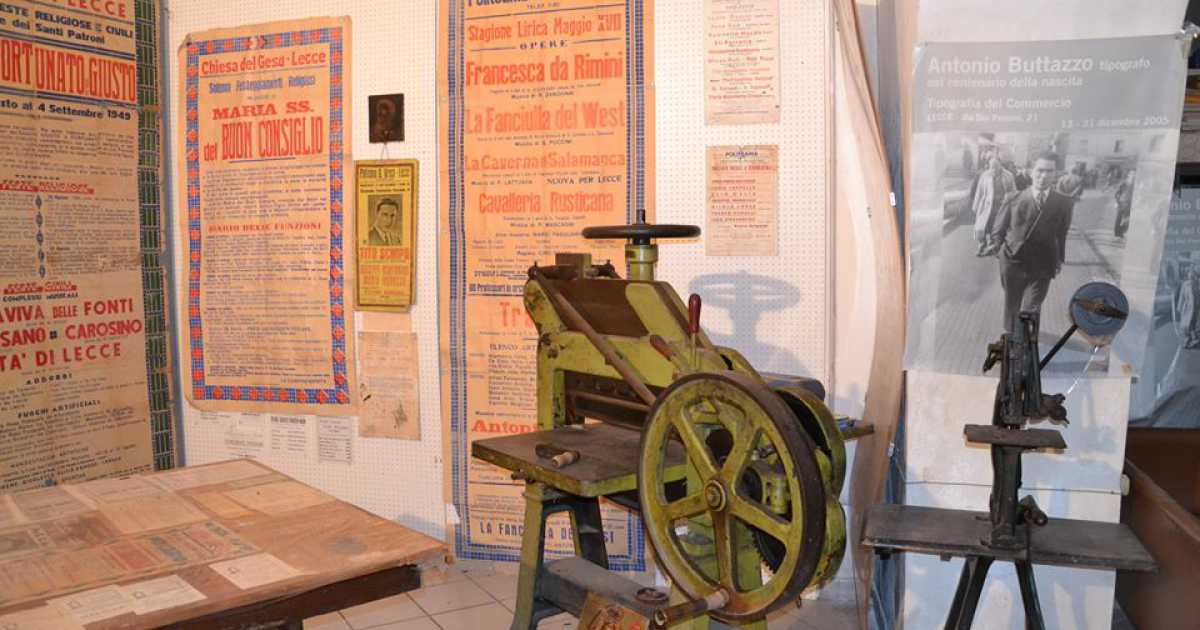
LECCE – Caratteri mobili, odore di inchiostro, macchine che si muovono a pedale o facendo girare manualmente una ruota: nella “Tipografia del commercio” di Lecce, il tempo sembra essersi fermato e ancora oggi si stampa come se l’avvento della produzione seriale e industriale non fosse mai sopraggiunto. A compiere il sortilegio è il 76enne leccese Alberto Buttazzo, figlio d’arte nel campo della tipografia: segue le orme dei suoi predecessori, quelle del nonno Umberto e del padre Antonio, numi tutelari della stampa salentina.
Siamo in via dei Perroni in pieno centro storico, nei pressi della barocca chiesa di San Matteo. Oltrepassato l’ingresso sormontato dall’insegna annerita del secolo scorso, ci si imbatte in un locale al pian terreno dalle alte volte e dalle possenti mura cinquecentesche che trasuda storia e arte da ogni angolo. Dai muri pendono manifesti e locandine di grande formato che annunciano a caratteri cubitali opere liriche e spettacoli cinematografici novecenteschi, mentre fanno bella mostra di sé nella sala antichi macchinari per la stampa e cassettiere lignee che racchiudono come uno scrigno prezioso i metallici caratteri mobili (vedi foto galleria).
Tutto ha inizio quando Umberto Buttazzo, il “proto” della stamperia del barone Giurdignano, come si usa dire nel lessico tipografico, cioè il capo operaio incaricato della distribuzione e dell’ispezione generale, nel 1926 sostenuto dal figlio Antonio si decide a creare una propria tipografia denominata “La teatrale”, con sede in via Dei Conti di Lecce. Già il nome scelto chiarisce bene in quale campo i due decidono di specializzarsi: la produzione di manifesti e locandine di spettacoli e concerti e in particolar modo quelli del tenore concittadino famoso in tutto il mondo, Tito Schipa, di cui Antonio è grande amico e profondo conoscitore.
«Alla morte di nonno Umberto prende definitivamente le redini dell’attività mio padre Antonio – ci racconta l’attuale titolare Alberto -. Nel 1934 mio padre trasferisce la stamperia in via Boemondo, sempre nel centro storico, con la nuova denominazione di “Tipografia del commercio”: è il segno dei tempi che cambiano e della volontà di aprirsi non solo al mondo dell’arte ma anche a quello produttivo e commerciale. Per esempio – chiarisce - si rende necessario aprire una succursale nel paese di Squinzano per rispondere alle numerose richieste dei viticultori locali. Si continua comunque a produrre locandine cinematografiche, si arriva a stamparne una al giorno in grande velocità, ma anche manifesti per le feste patronali, facsimili di schede elettorali e comunicati politici che all’epoca precedevano l’uscita dei giornali e rappresentavano il primo strumento di informazione».
Ma lo stampatore Antonio è soprattutto un innovatore all’avanguardia per i suoi tempi. Frequenta ogni anno la più importante fiera nazionale nel campo editoriale, la Fiera di Milano e riceve spesso riconoscimenti importanti. E viene ricordato in particolar modo per l’invenzione dei manifesti formato “elefante”: di grandi dimensioni e con grandi caratteri ottenuti inchiostrando i caratteri mobili e sottoponendoli a pressione sul telaio da stampa su cui è appoggiata la carta e facendo indugiare il rullo della macchina quanto più possibile sino ad ottenere l’effetto ingrandito. Ciò è possibile perché Antonio si rende conto del cambiamento dei tempi e decide di meccanizzarsi acquistando le nuove macchine tipografiche “piane” con il volano manuale con cui può controllare il tempo di pressione. Si tratta esattamente delle stesse macchine che ancora oggi utilizza l’erede Alberto, ignorando cosa sia una stampa laser o digitale.
Lecce, la tipografia dove si stampa ancora con i caratteri mobili
«Mio padre ci ha lasciati inaspettatamente nel 1957 a soli 52 anni – continua Alberto -. Io avevo appena 18 anni e raccoglierne l’eredità in un momento di profonda crisi della richiesta a causa della concorrenza della produzione seriale che si andava diffondendo, non è stato affatto facile. Eppure non ho chiuso la stamperia neanche per un giorno. Ho dovuto però licenziare i quattro, cinque operai impiegati e fare tutto da solo. E incredibilmente è quello che riesco a fare ancora oggi dopo aver trasferito definitivamente nel 1991 la sede della tipografia in quella attuale in via dei Perroni. Ho volutamente scelto di continuare a usare i macchinari acquistati da mio padre: una gigantesca “Marinoni” tipografica piana con volano manuale dell’800, una “Pedalina” degli anni 20, funzionante tramite pedale appunto (vedi video), una pressa idraulica per fustellare degli anni 50 e una pirottinatrice a caldo, anch’essa degli anni 50, per produrre come il nome stesso indica, pirottini per dolci».
Ma soprattutto Alberto si è specializzato nella stampa “artistica”, per esempio nella produzione di cliché in linoleum e cioè di matrici che trasferiscono su un supporto in carta l’inchiostro rilasciato da un rullo e costituiscono vere e proprie opere d’arte contemporanea. Sono attualmente esposte infatti in musei di Parigi e di Berlino copie del cliché con il gioco di lettere che lo stesso Carmelo Bene ha voluto, recandosi in prima persona nell’officina e mettendosi a lavorare lui stesso, per il suo spettacolo teatrale “Gregorio Cabaret dell’800”, rappresentato a Lecce nel teatro Apollo nei primi anni 60.
«La tipografia è oggi meta di numerosi turisti che giungono qui ad apprezzarla da tutto il mondo – conclude Alberto -. Ma i primi a dimenticarsene e a non saperla valorizzare sono proprio i cittadini leccesi incapaci di riconoscerne il ruolo di fondamentale testimonianza storica della vita culturale della città di Lecce e della sua provincia. Per ora ci sono io a custodire gelosamente questo tesoro ma dopo di me verrà sepolto definitivamente? ».